文字塾展
文字塾は、ヒラギノ書体、游書体ライブラリーなど100書体以上の制作に携わり、字游工房代表取締役を務める鳥海修氏が主催する1年を通して、自分がデザインした明朝体のひらがな、カタカナをフォント化して成果を展示会で発表する塾。
第6期文字塾展「すきこそもじの上手なれ」
2018年06月03日(日)~6月09日(土)に文字塾第6期生11名の展示される。展示会タイトルは「すきこそもじの上手なれ」。
▼第6期文字塾展「すきこそもじの上手なれ」展示会場所
人形町ヴィジョンズ
▼第6期文字塾展「すきこそもじの上手なれ」参加者
Acra Koh(アクラ コウ)/淺岡真世/上杉望/木内陽/坂野徹/新海真司/隅芙蘭都/遠矢良彦/松葉菜摘/吉田大成/綿引麻子(五十音順、計11名)
▼第6期文字塾展「すきこそもじの上手なれ」展示日程
2018年6月3日(日)~6月9日(土)
第五期文字塾展 みんな極めたかんじもね
2017年6月4日から10日まで人形町ヴィジョンズで開催されている書体展示会「第五期文字塾展 みんな極めたかんじもね」。
「第五期文字塾展 みんな極めたかんじもね」は、著書「文字を作る仕事」が第65回日本エッセイスト・クラブ賞を受賞するなど話題の書体設計士・鳥海修氏が主宰する文字塾第五期生13名による「かな書体」の展示会。
文字塾では1年間を費やし、自分自身の平仮名と片仮名をデザインし、フォント化。その成果をこの展示会で発表するというスタイルの塾になっている。
▼塾生
相川ひかる/淺岡真世/池田平多/小澤祥/木内陽/木村昌司/髙橋謙吾/土井遼太/舟瀬純子/松葉菜摘/山口萌子/山嵜重則/吉田大成(五十音順計13名)
あしらい明朝 土井遼太氏
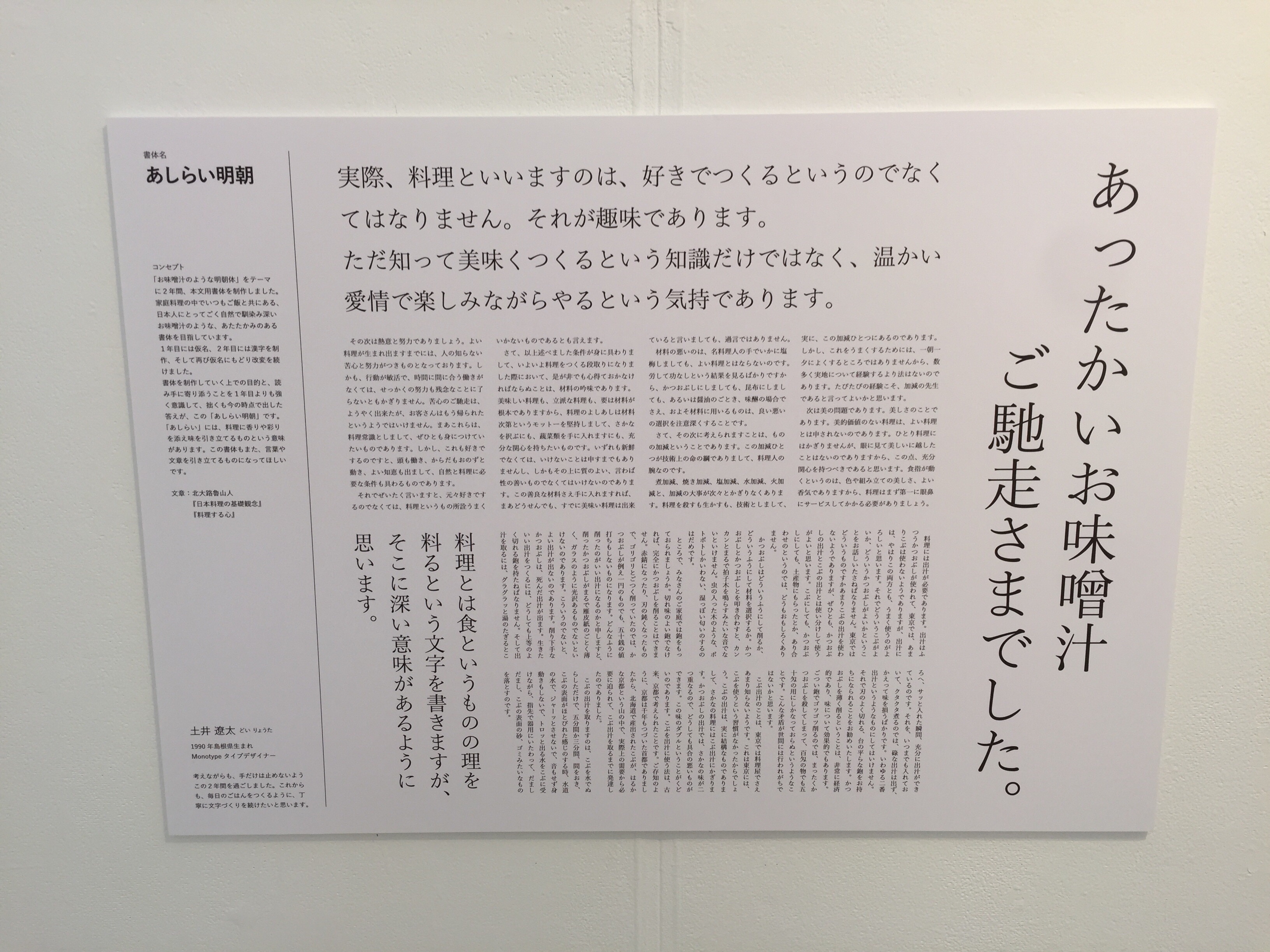
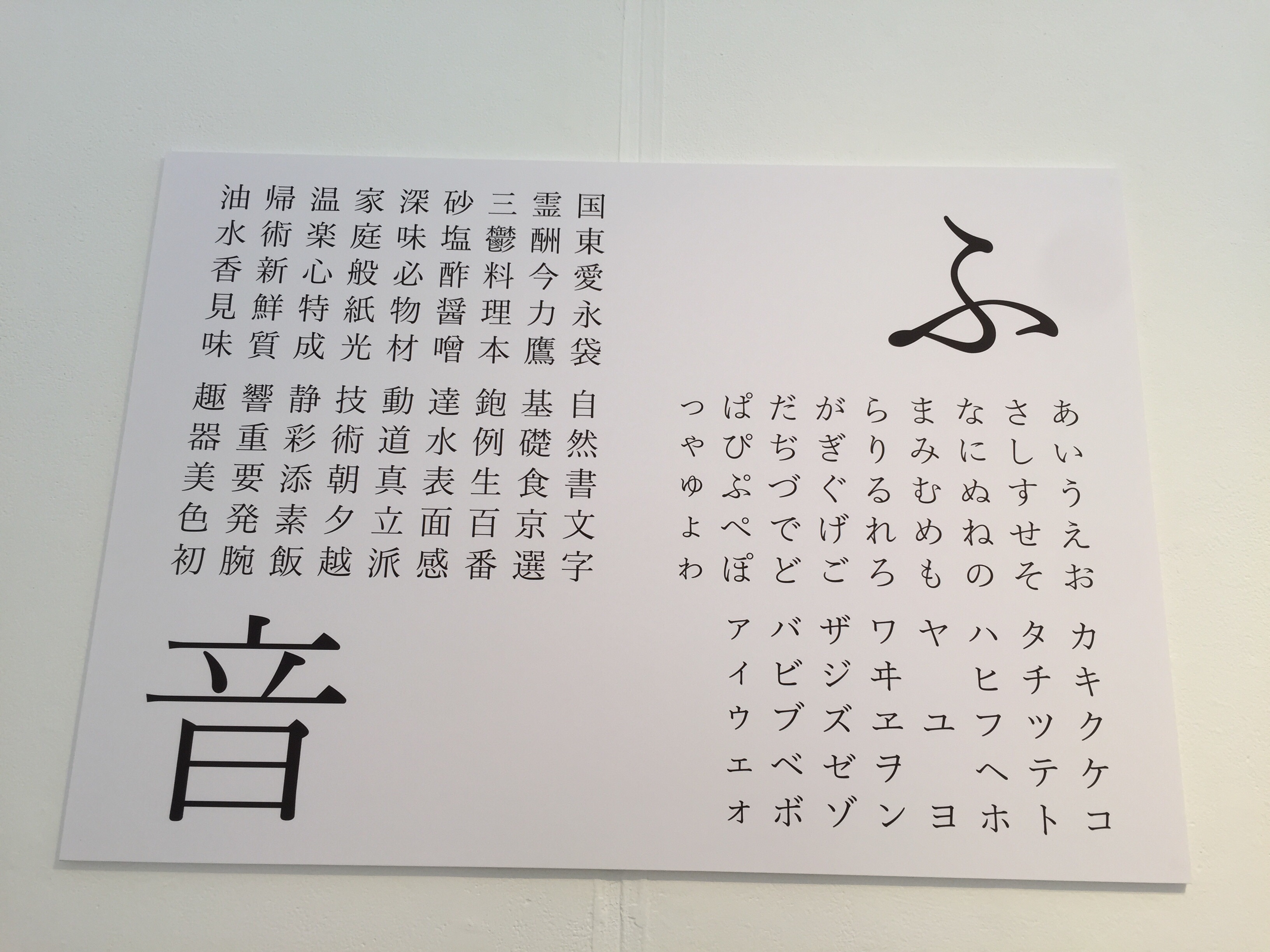
モノタイプ社の和文書体「たづがね角ゴシック」のデザインを手掛けた書体デザイナー土井遼太氏は2年連続で塾に参加している。今後、あしらい明朝が「たづがね明朝体」とどう繋がっていくのかも楽しみ。
あめざき 浅岡真世氏
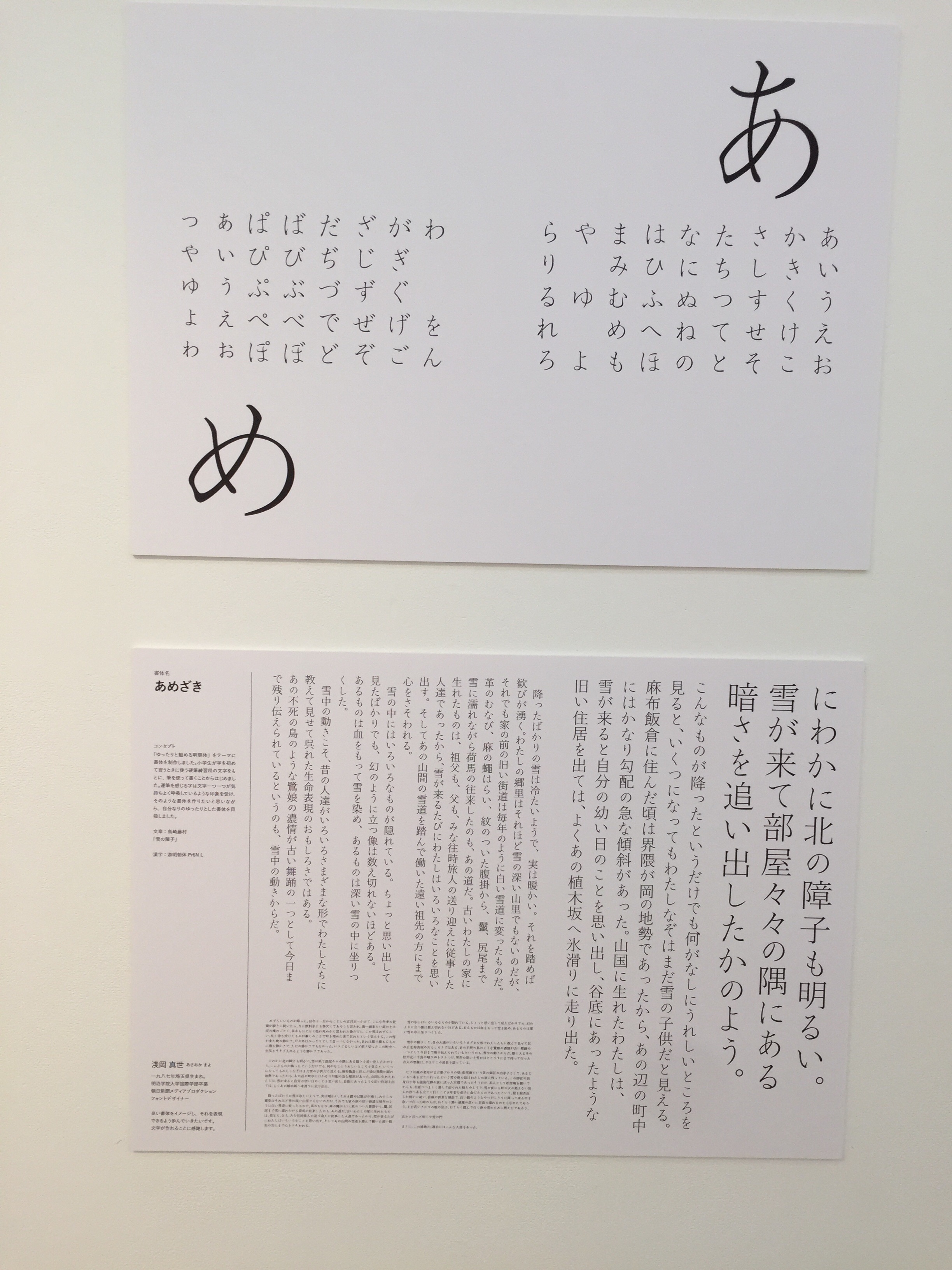
レスラー明朝 相川ひかる氏
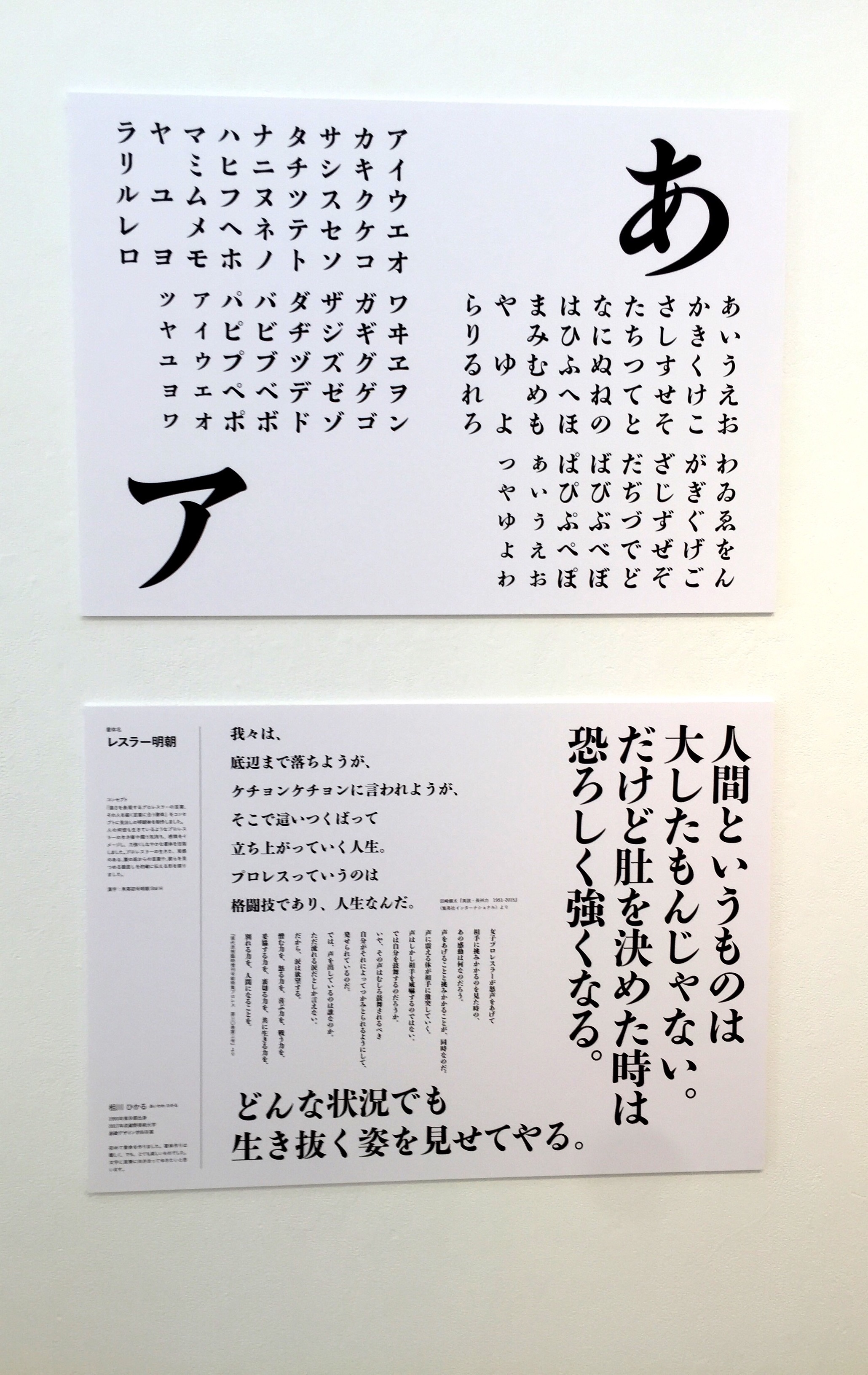
コンセプトが面白い。特に「や」の文字からプロレスラーを感じる。
いてなぎ 山口萌子氏
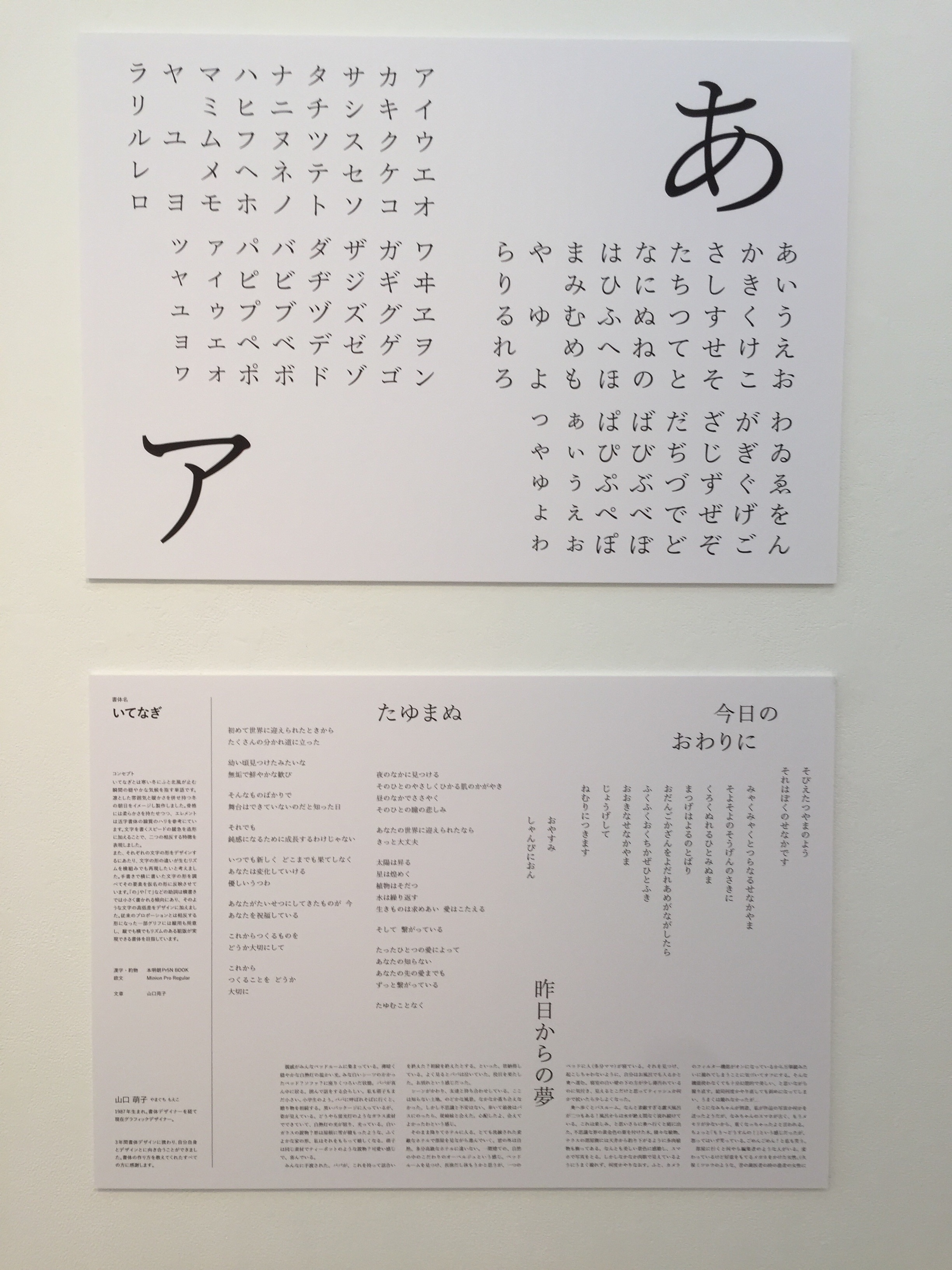
たいらの 木村昌司氏
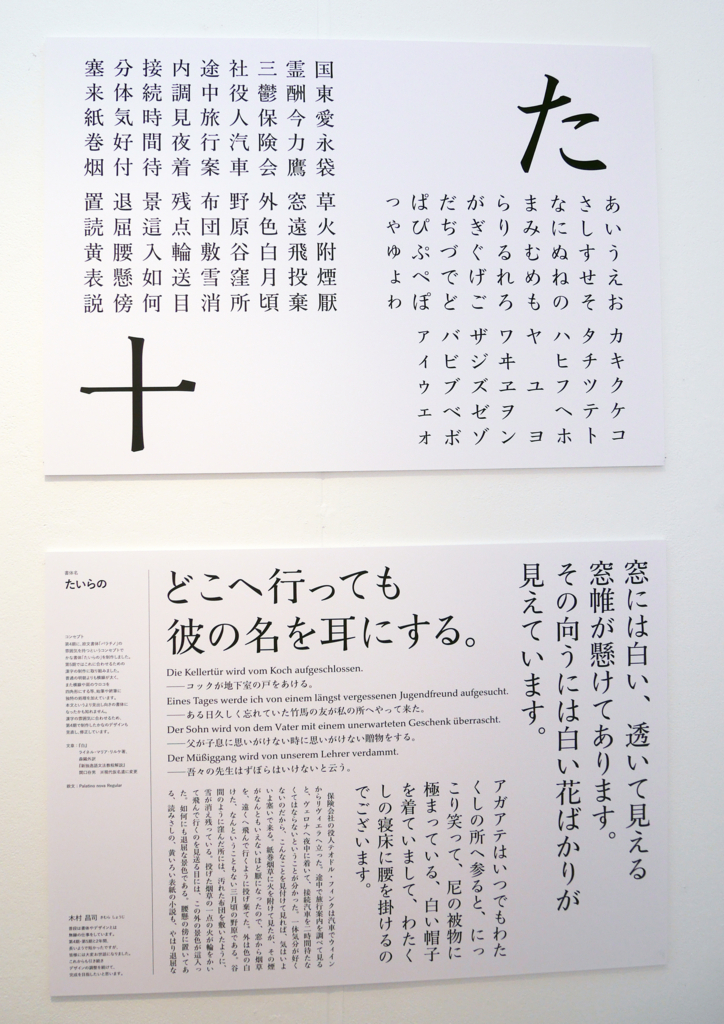
朝露 小澤祥氏
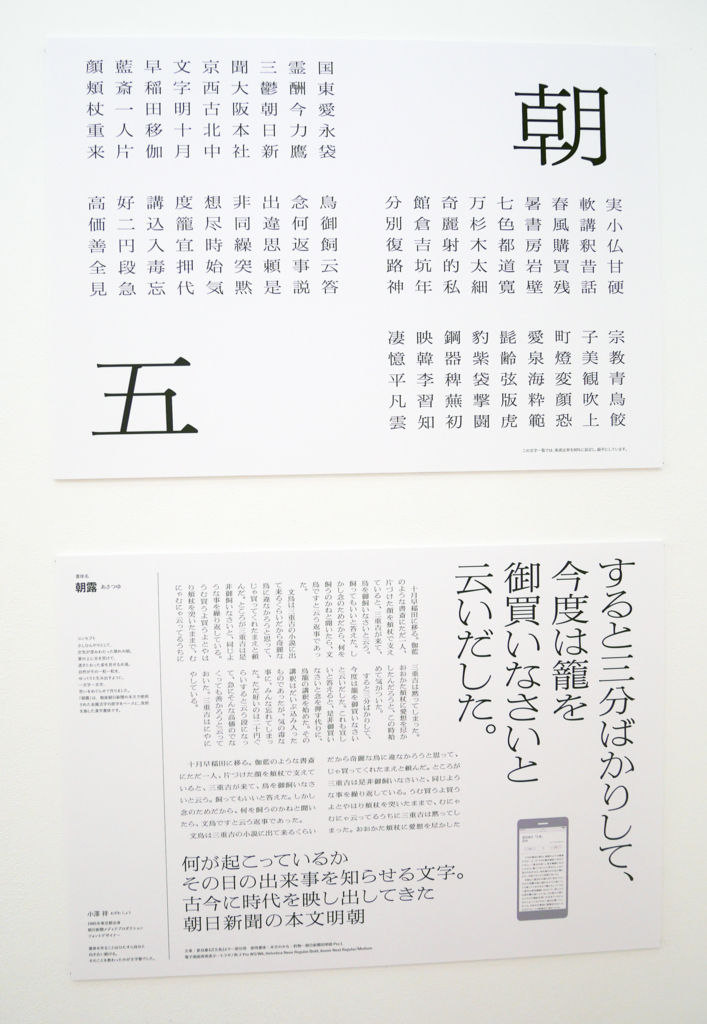
朝日新聞社フォントデザイナー小澤祥氏は3年連続の受講となる。
みなも 高橋謙吾氏
いろみん 山嵜重則氏
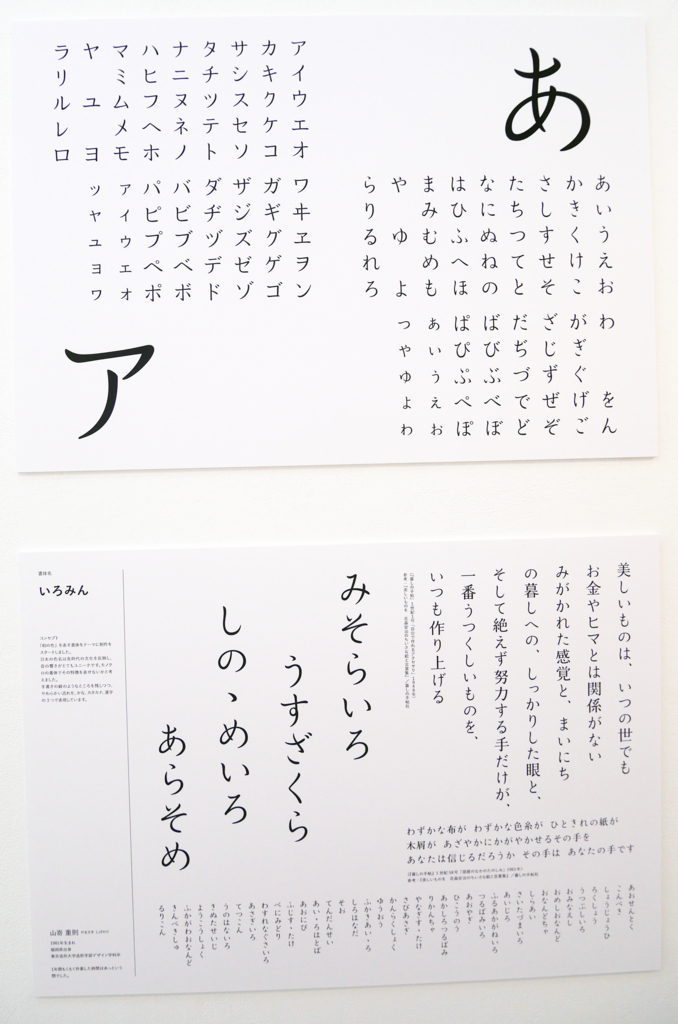
はくれい 吉田大成氏
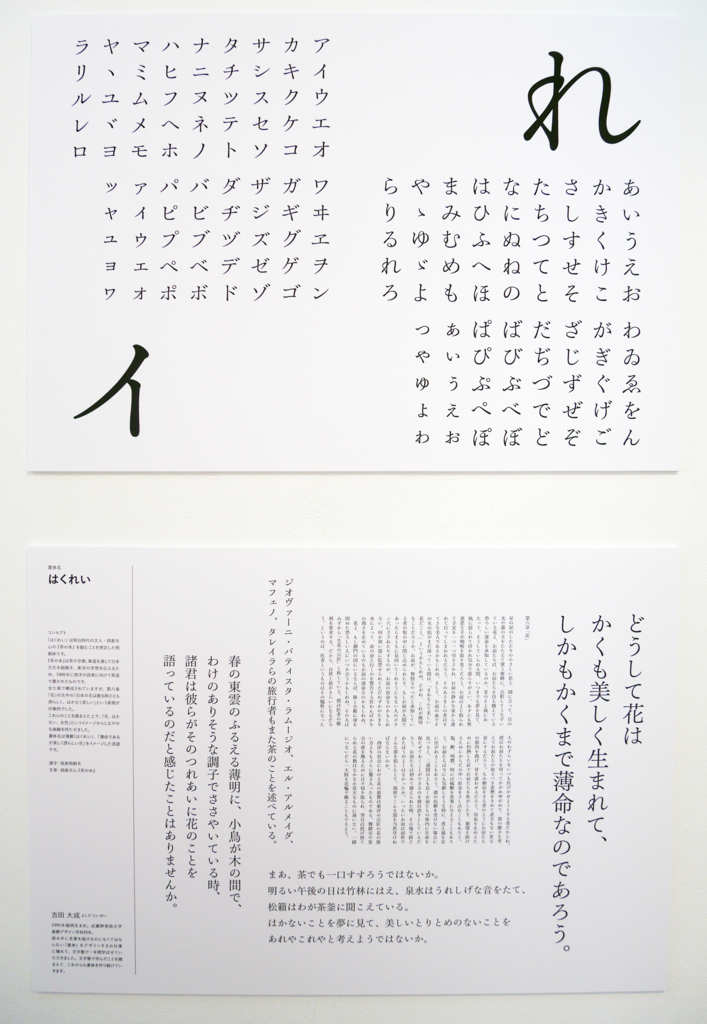
さみだれ 木内陽氏
かがよい明朝 松葉菜摘氏
松葉菜摘氏も2年連続での受講。3年目も受講予定らしい。
レタリング 池田平多氏
池田平多氏も2年連続の受講。昨年の作品スーボのような変体仮名「ヘータ」インパクトもすごい。
前年に行われた第四期文字塾 14人のかな書体「こんなにたのしくていいのかな」では、塾生・松村潤子氏の作品「しまなみ」がモリサワが開催した2016年タイプデザインコンペティションにおいて、モリサワ賞和文金賞とモリサワからの製品化を前提とした明石賞を受賞している。
松村氏は、第四期文字塾で、初めて書体デザインに取り組み、現在は製品化へ向け、モリサワ文研株式会社と追加分となる漢字などの制作を進めている。
▼しまなみがモリサワパスポートに収録されるのは2018年あたりだろうか。
文字塾展 第四期 14人のかな書体
▼「文字塾展 第四期 14人のかな書体」展示作家
池田 平多/石川 とも子/遠藤 隼斗/小澤 祥/狩野 宏樹/木村 昌司/田中 裕梨/土井 遼太/遠矢 良彦/長谷川 文香/平井 玲子/舟瀬 純子/松村 潤子/水野 博之
人形町ヴィジョンズ
▼「文字塾展 第四期 14人のかな書体」展示会期日程
2016年06月05日(日)~6月11日(土)
▼鳥海修氏参考出品仮名
あしらい明朝(2016年) 土井遼太氏
温故がな 狩野宏樹氏
こくたん 遠矢良彦氏
おうじさま 長谷川文香氏
たいらの 木村昌司氏
しまなみ 松村潤子氏
つらなり 遠藤隼斗氏
ばいこう 小澤祥氏
ヘータ 池田平多氏
よこなり 石川とも子氏
れいめい 舟瀬純子氏
れん 田中裕梨氏
風鈴 平井玲子氏